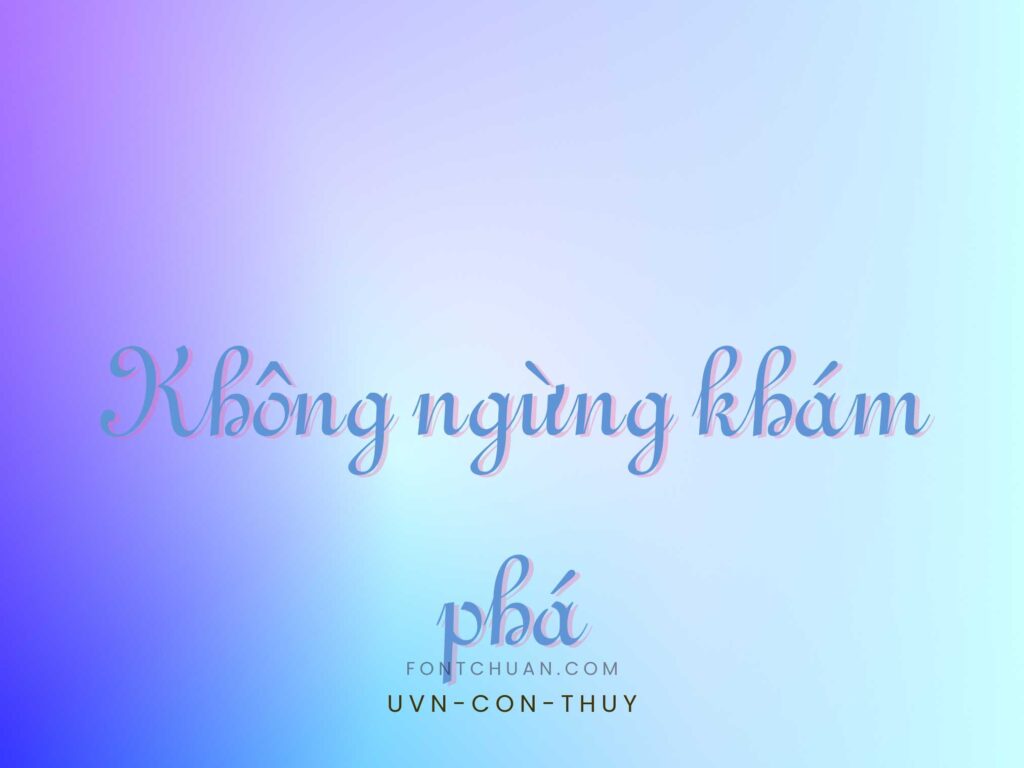
Font UVN Con Thuy Việt Hóa
UVN Cỏ Thụy là một phông chữ thư pháp mang đậm phong cách nghệ thuật viết tay truyền thống. Được thiết kế với các nét bút lông mềm mại và uyển chuyển, phông chữ này tạo nên sự thanh thoát và tinh tế cho các tác phẩm thiết kế. UVN Cỏ Thụy hỗ trợ đầy đủ các ký tự tiếng Việt, giúp người dùng dễ dàng sử dụng trong các dự án sáng tạo liên quan đến văn hóa Việt Nam.
Với thiết kế độc đáo và nghệ thuật, UVN Cỏ Thụy phù hợp cho các ứng dụng như thiệp mời, tiêu đề sách, thiết kế logo và các ấn phẩm nghệ thuật. Trong lĩnh vực sự kiện, phông chữ này có thể được sử dụng trong các dịp như lễ hội, lễ cưới và các sự kiện văn hóa. Ngoài ra, UVN Cỏ Thụy còn là một Font chữ ảnh cưới lý tưởng, giúp tạo điểm nhấn tinh tế cho các thiệp cưới, album ảnh hay các sản phẩm kỷ niệm, mang đến sự lãng mạn, sang trọng và nghệ thuật cho các thiết kế. Font này cũng thích hợp cho các ngành nghề như thiết kế đồ họa, nghệ thuật trang trí và xuất bản.